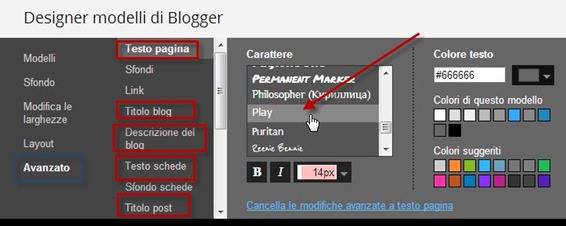
Come personalizzare i caratteri in un blog di Blogger modificando il modello e scegliendo la famiglia di font oltre che la loro dimensione.
A seguito di modifiche grafiche apportate al sito ho pensato anche di personalizzare la famiglia di caratteri del blog. Questa operazione è solo apparentemente semplice perché invece può nascondere diverse insidie. La scelta stessa dei font da utilizzare non è da sottovalutare. I caratteri sono suddivisi in due grandi categorie, quelli con le Grazie e quelli senza Grazie. Si usa più spesso la terminologia inglese che è diventata internazionale sans-serif che poi deriva chiaramente dal francese.
È comune convinzione che i caratteri con le Grazie siano più facilmente leggibili in un foglio di carta mentre quelli senza Grazie trattino meglio gli occhi nella lettura al computer di grandi blocchi di testo. La scelta è ovviamente personale e penso si debba coniugare un certo grado di originalità con la facilità di lettura da parte dei navigatori.
In questo articolo non voglio affrontare il tema della personalizzazione dei caratteri attraverso i 700 font di Google che ho già affrontato in un altro post. Tale metodologia tra l'altro può essere estesa anche ai blog a Visualizzazione Dinamica. Non mi occuperò neppure di come scaricare font dal web e usarli nel blog con @font-face, tema che ho già trattato. Mi limiterò a mostrare come modificare i font usando quelli messi a disposizione dalla piattaforma Blogger. Il modo di procedere è alquanto diverso a seconda del tipo di modello che abbiamo e dei widget che vi abbiamo installato.
PERSONALIZZARE I FONT CON DESIGNER MODELLI
Se si possiede un blog Dynamic Views o se si sta creando il modello dall'inizio allora è consigliabile usare il Designer Modelli che ci consente di farlo in modo semplice e efficace. Si va su Modello > Personalizza > Avanzato e si configurano tipo, dimensione e colori dei caratteri
Si possono settare famiglia di caratteri, colore del testo, dimensione dei font per molti elementi del sito quali il corpo della pagina, il titolo e la descrizione del blog, il testo delle schede, il titolo dei post e i gadget. In basso si vedrà l'anteprima del sito dopo ogni modifica. Per renderle effettive bisognerà andare in alto a destra su Applica al blog.
MODIFICARE I FONT IN UN TEMPLATE PERSONALIZZATO
Se si ha un modello che abbiamo già personalizzato o che addirittura abbiamo scaricato da internet può essere rischioso usare questo procedimento perché cliccando su Personalizza possono essere azzerate molte modifiche che abbiamo faticosamente aggiunto come i menù o altre personalizzazioni del modello. Quindi prima di usare il Designer Modelli è consigliabile salvare il template per un eventuale ripristino.
Vediamo come procedere in questa operazione in modo manuale. Naturalmente va comunque sempre prima salvato il template. Si va su Modello > Modifica HTML e si clicca sulle freccette nere di  <b:skin>
in modo da visualizzare tutti i fogli di stile. Andiamo subito a vedere se in body { c'è una riga del tipo font: $(body.font); . Se è presente vuol dire che i parametri dei font sono stati settati nella sezione /* Variable definitions */ con un codice simile a quello seguente
In sostanza i font del corpo del testo sono dati dal valore che prende body.font. Nell'esempio precedente è
La parte del codice in default mostra invece quelli che erano i parametri iniziali del modello e non vanno toccati. Quindi per modificare i caratteri basta cambiare i pixel della dimensione e la famiglia di font oltre a settare un nuovo colore in value="#666666".
Questa operazione va ripetuta per gli altri elementi del template. Per esempio header.font per il titolo del blog oppure per tabs.font che si trova in un codice come questo
per configurare la dimensione e il tipo di font dei widget. Un altro codice è il seguente
Un simile procedimento può essere fatto anche con gli altri selettori.